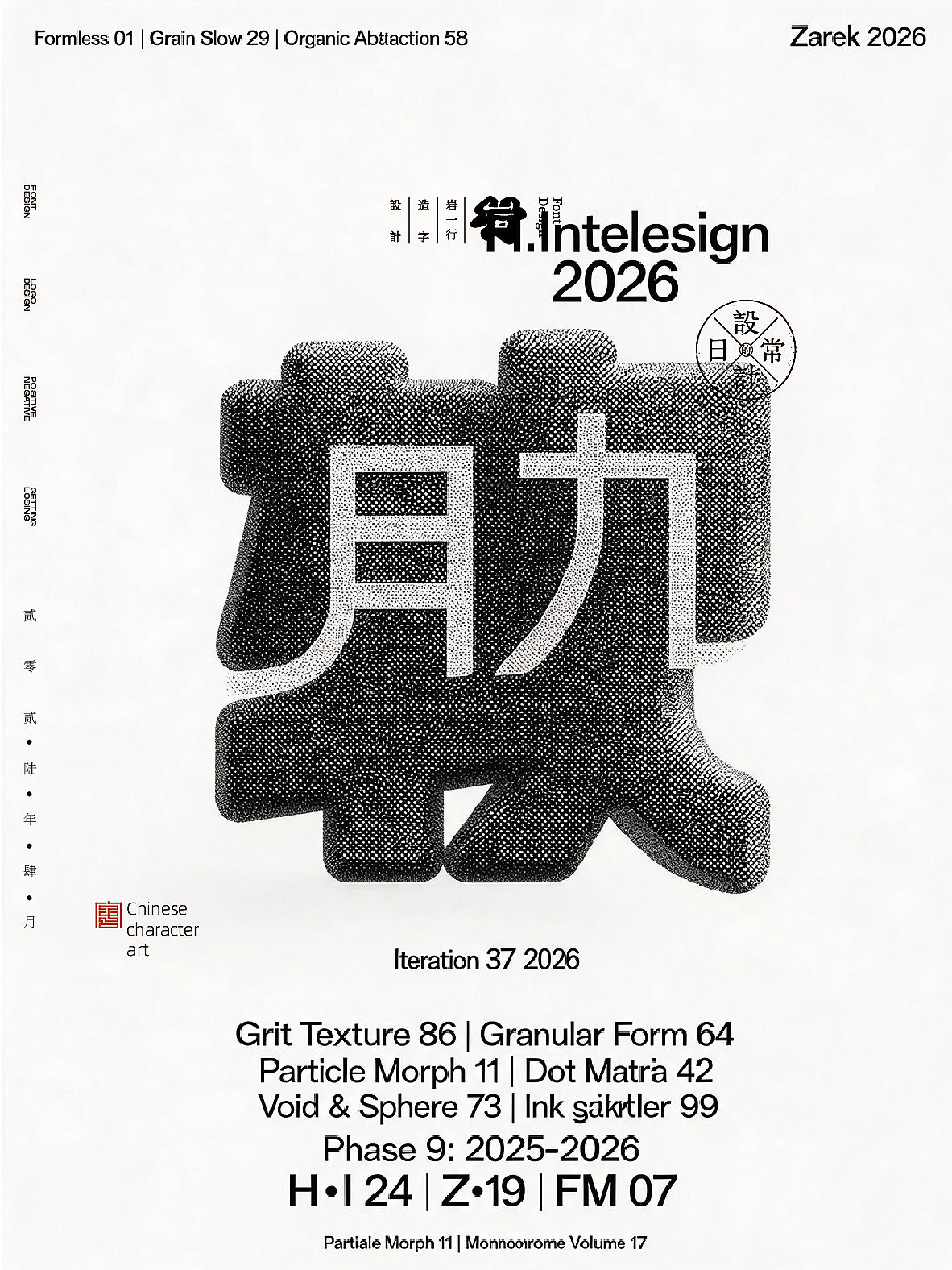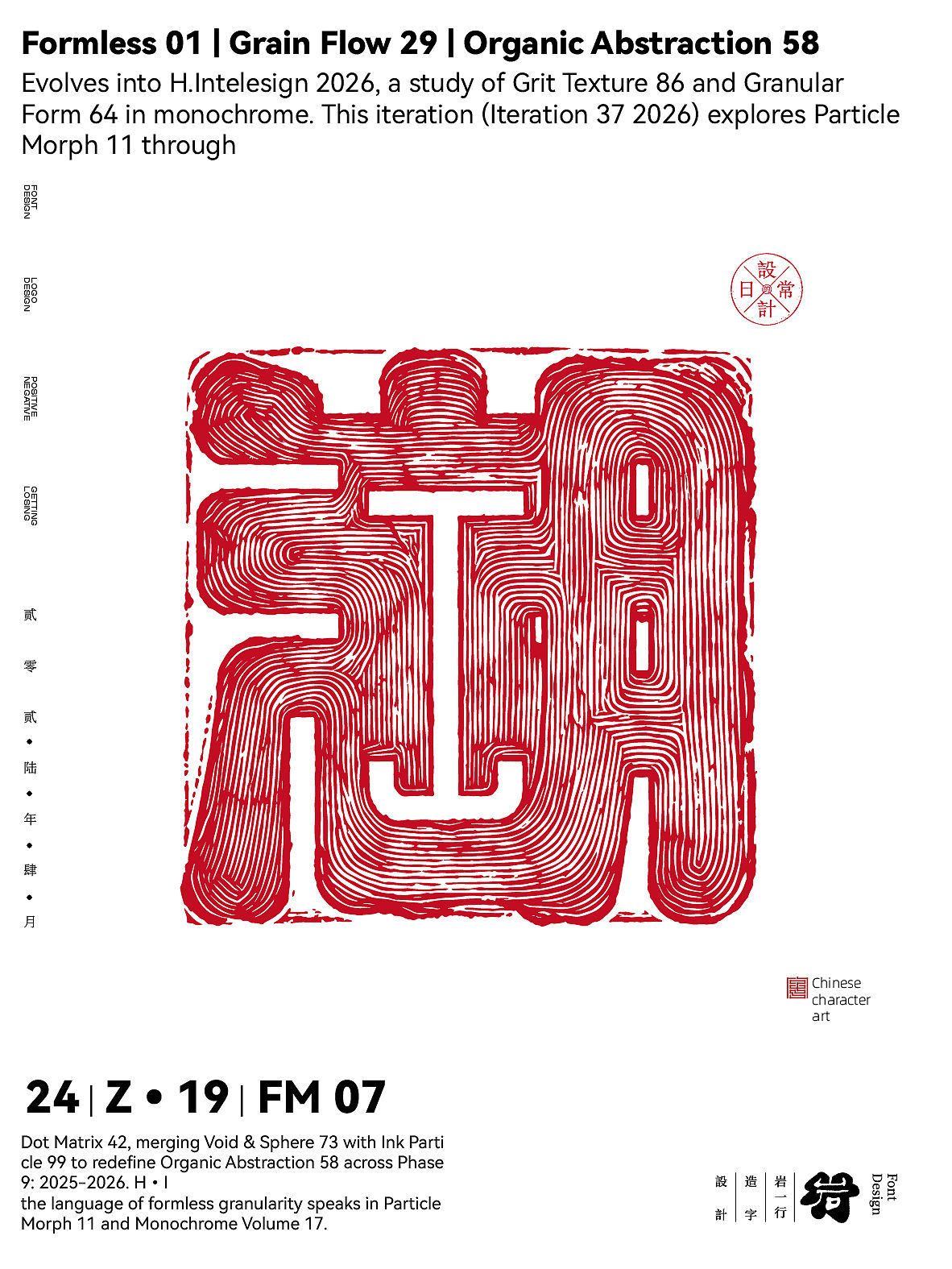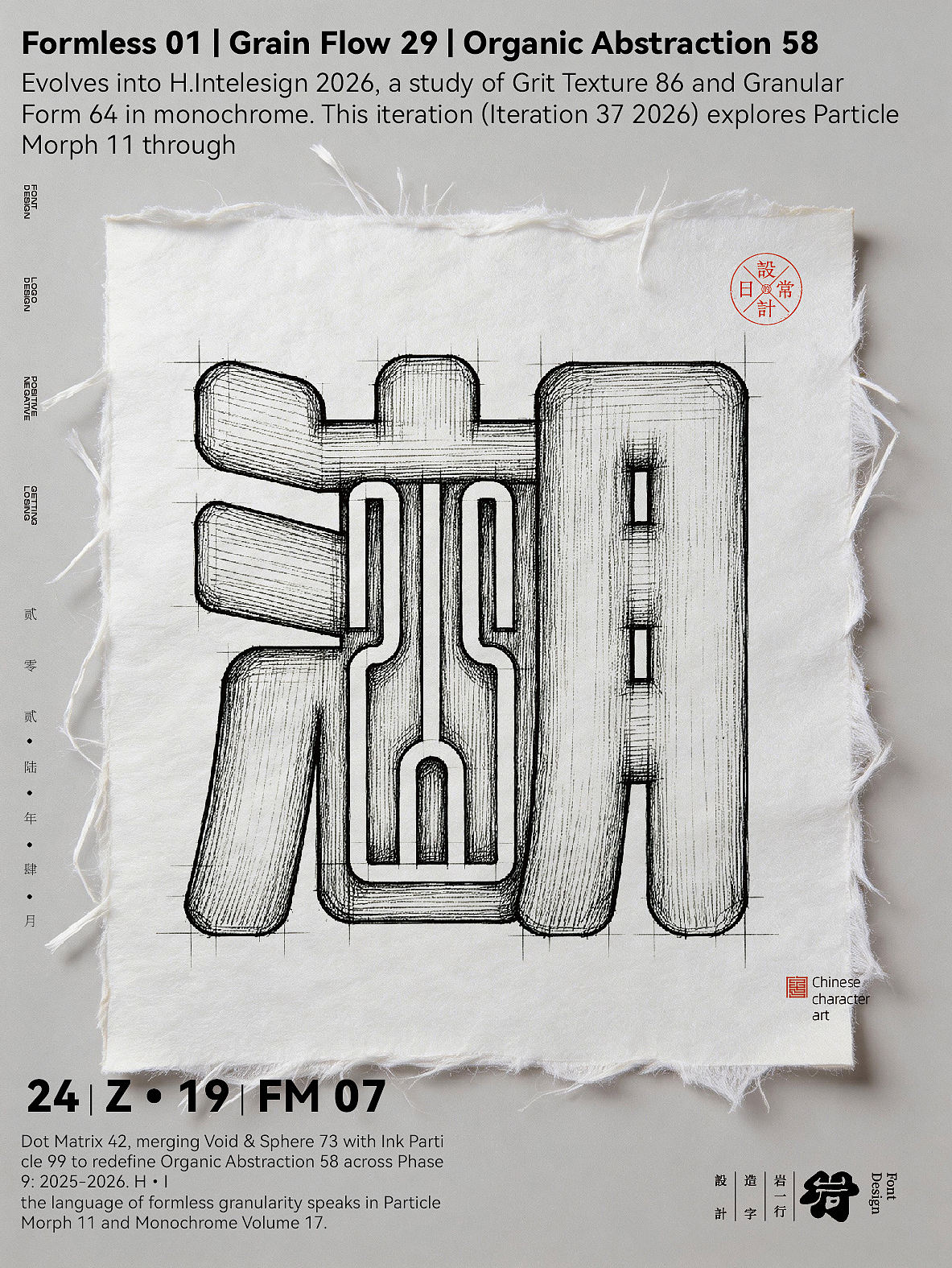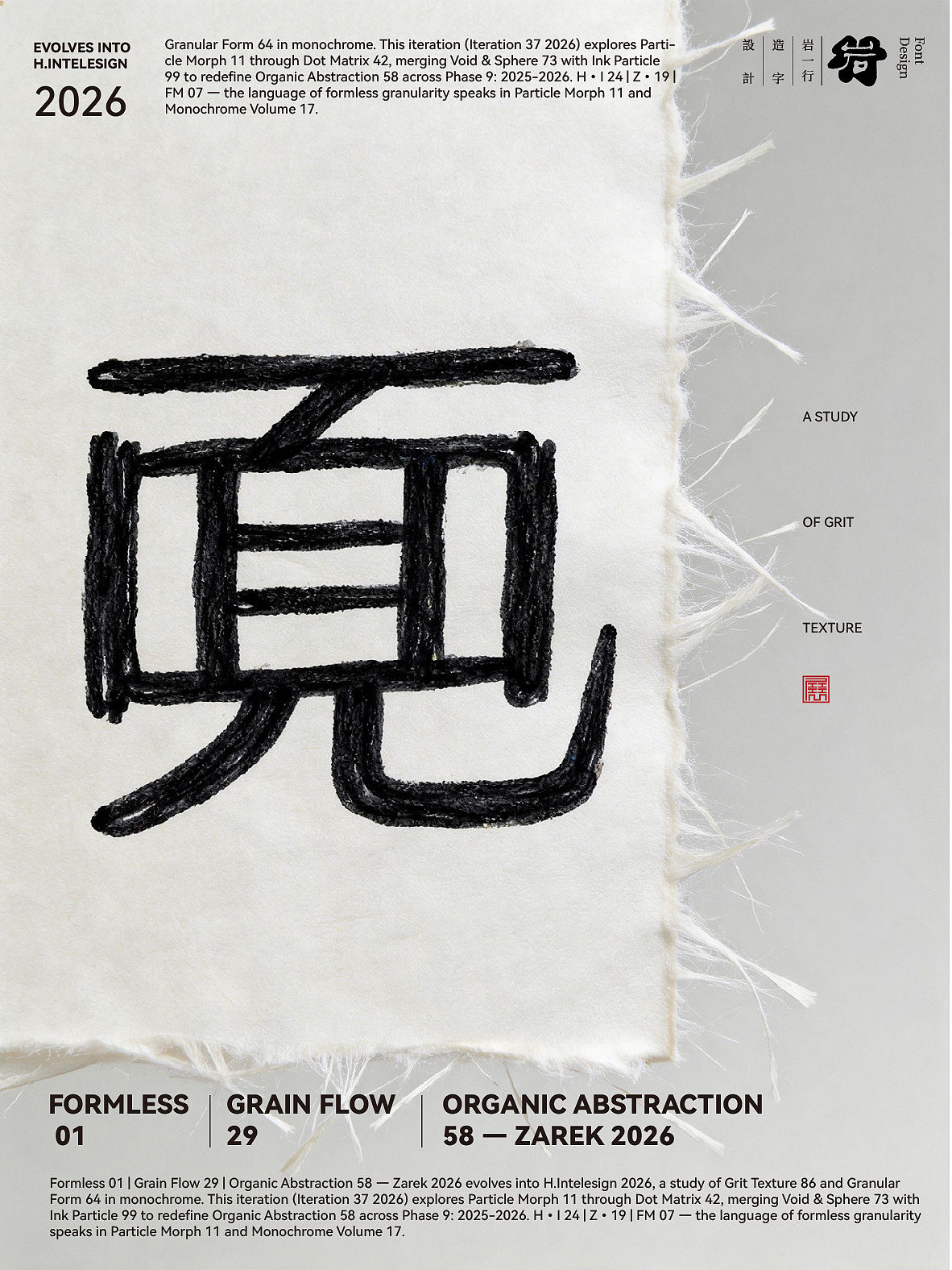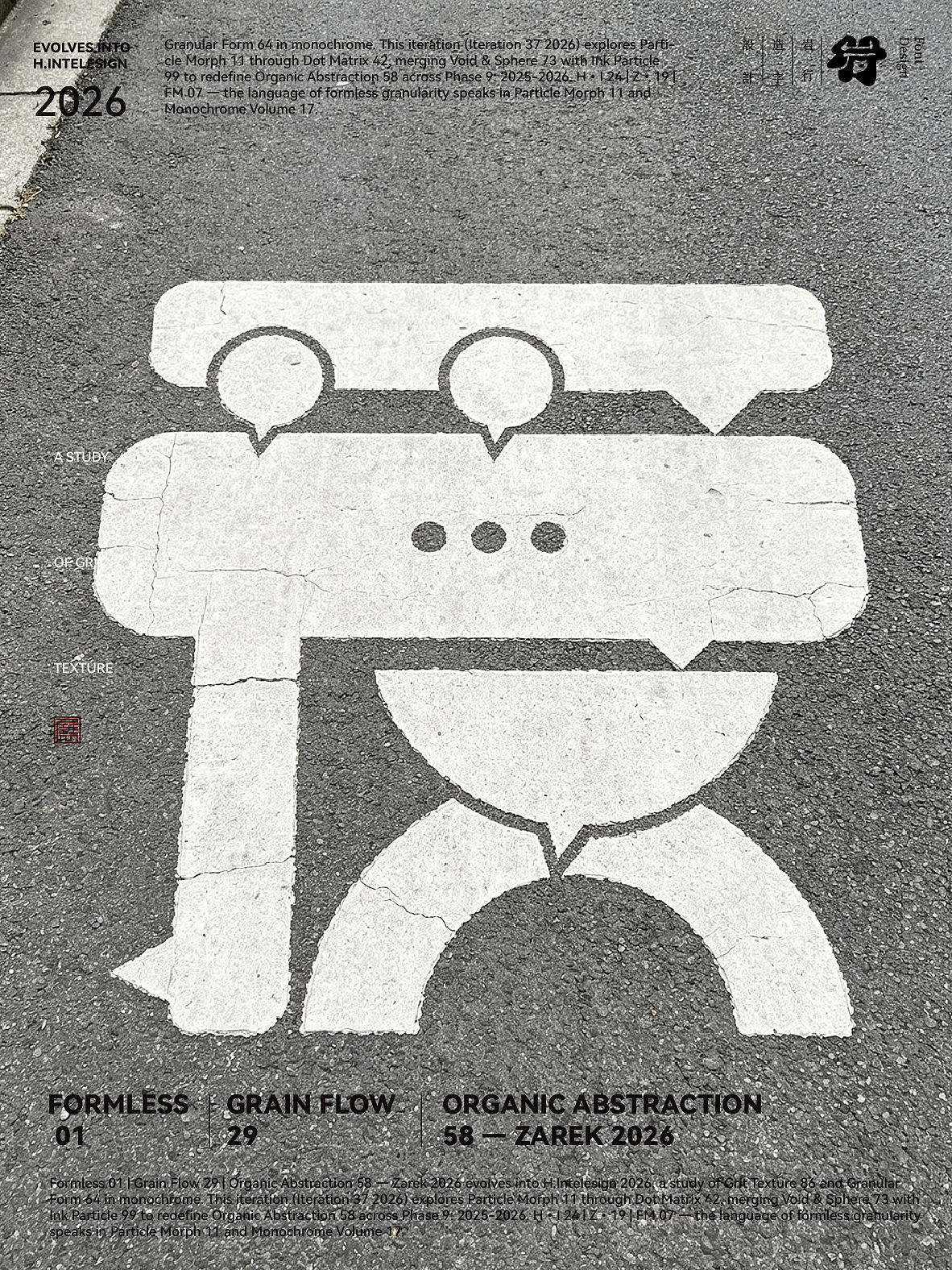
又一个三十天,表意合一、字形共生 的双重设计。
合体字区别于普通字体拼接,词义关联性是组合的先决条件,
只有内涵相通的汉字,合体之后才具备文化逻辑。在日常练习中,
我优先筛选寓意呼应的字词组合,再从汉字部首、起收笔细节寻找融合点,
规避字义割裂却强行合体的问题。
我还对比古今合体字变化,古代合体字偏重实用祈福,字形紧凑厚重;
现代合体字更适配视觉设计,结构可以适度简化。
持续打磨,文化内涵是合体字的灵魂,结构优化是外在表达,二者缺一不可。